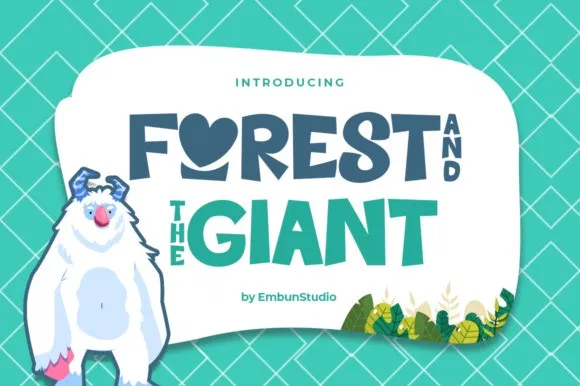
A Forest & The Giant Font é uma elegante escolha para quem busca um estilo visual moderno e amigável que combina a rusticidade das florestas com a personalidade alegre de seres grandes. Manufacturada pela EmbunStudio, esta fonte de exibição oferece um peso forte e aprimorado, garantindo uma ilustração clara em qualquer aplicação. Suportando não só o alfabeto inglês mas também uma ampla gama de idiomas, incluindo números e sinais de pontuação, é ideal para criações que exigem um toque encantador. Esta fonte é perfeita para quem quer dar um ar descontraído a designs relacionados à animação ou jogos infantis, mas também se encaixa perfeitamente em qualquer obra artística que busque uma pontada de diversão e brincadeira na linguagem visual.